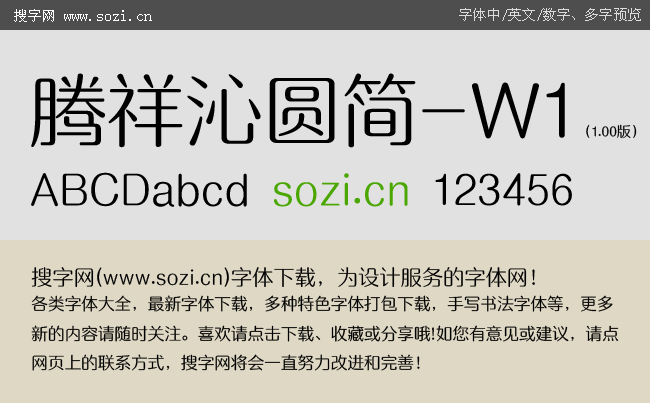
騰祥沁圓簡-W1
搜字網(wǎng)提供一款非常藝術(shù)的騰祥沁圓簡-W1下載,騰祥沁圓系列字庫是騰祥公司自主精心設(shè)計開發(fā)的藝術(shù)字體,其中W1為纖黑,筆畫規(guī)范精致、柔美大方、排版流暢易于閱讀,適用于正文、屏顯、產(chǎn)品設(shè)計特別是女性產(chǎn)品類設(shè)計及包裝印刷、廣告設(shè)計、平面設(shè)計、書籍報紙等領(lǐng)域。